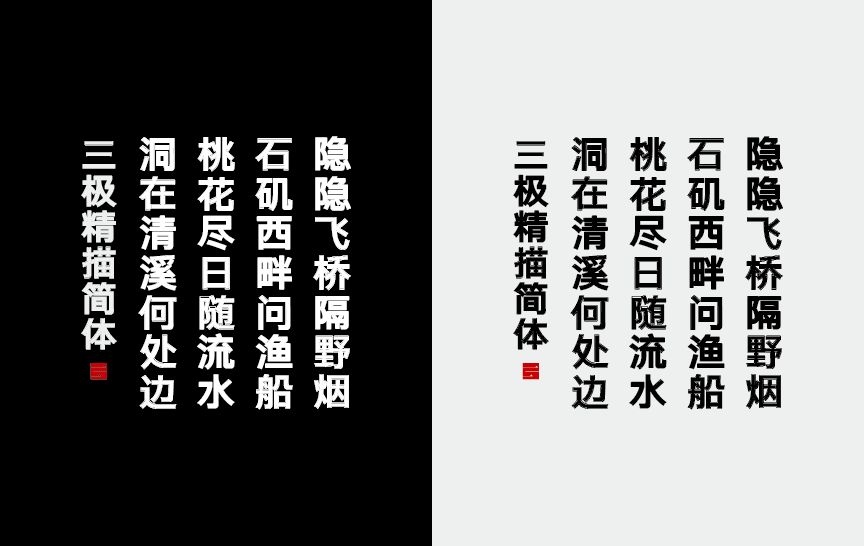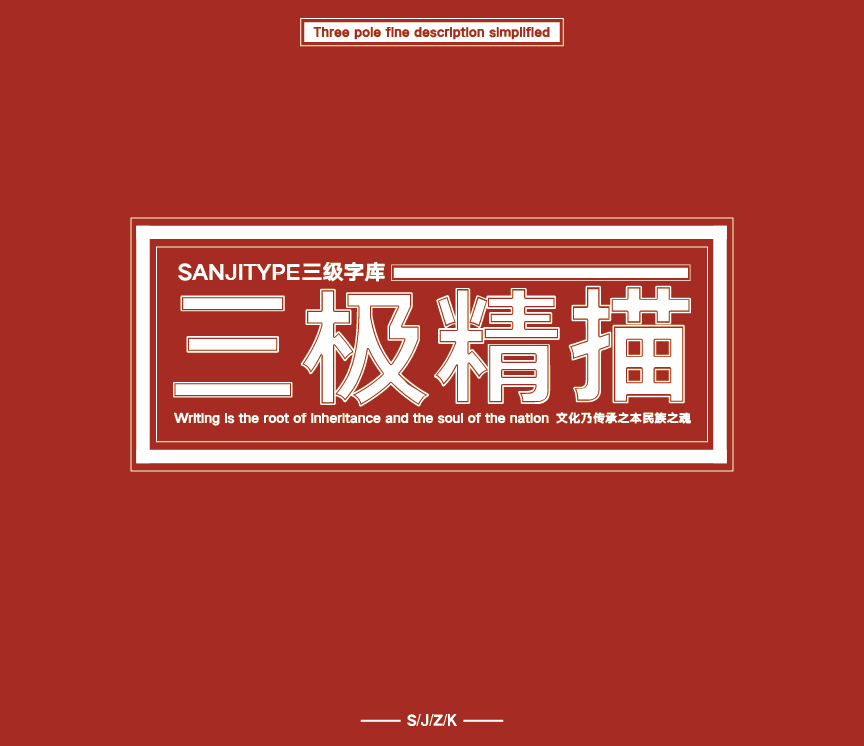
字体名称:三极典黑描边简体
设计师:罗碧霞,庞丽珊
三极典黑描边简体是一款特效字体,字形清新,结构严谨,布白均匀,中宫偏大,重心稳定。适当缩小字面大小、加大默认字距、增强了字体的识别性,使得版面更加生动。字形更加赋予变化。适用于各类便携式屏幕的系统嵌入字体,使其形态丰富,更适用于传统印刷媒介的标题与正文排版。在品牌形象设计中作为logo设计性文字视觉效果更佳。
适用媒介:报纸、杂志、书籍、广告、标志、宣传册、空间导视、包装、影视、屏幕显示、交互设计。